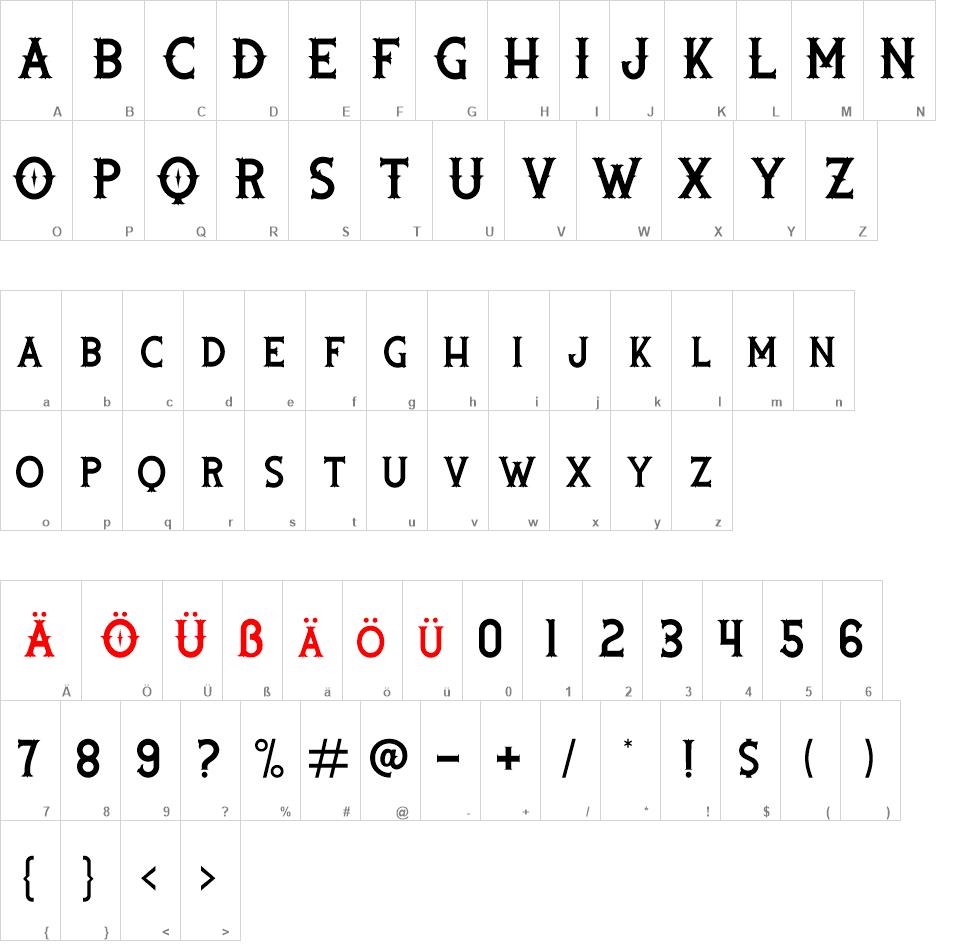
Rooters
Rooters ist eine Mischung aus klassischen Baseball-Buchstaben und ein wenig Einfluss auf die Tätowierung.
Tolle Ergänzung für Ihre Schriftenkollektionen im Vintage-Stil.
Erhältlich in zwei Ausführungen (Regular und Slanted).